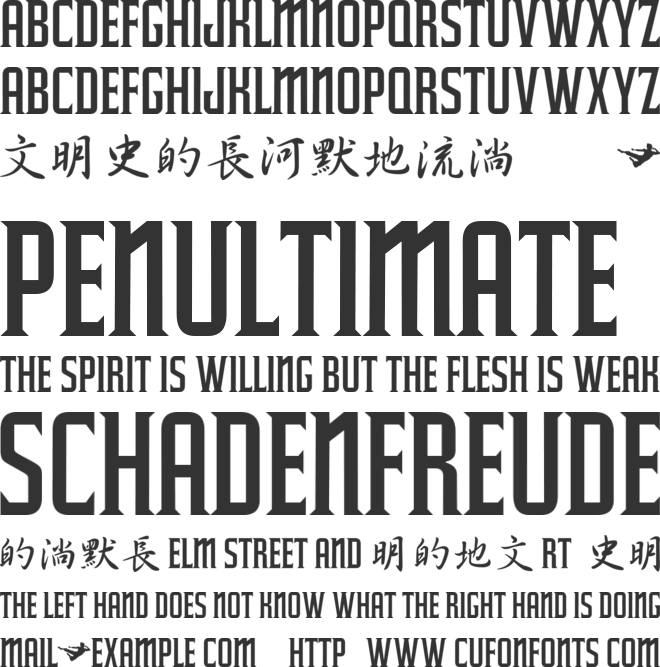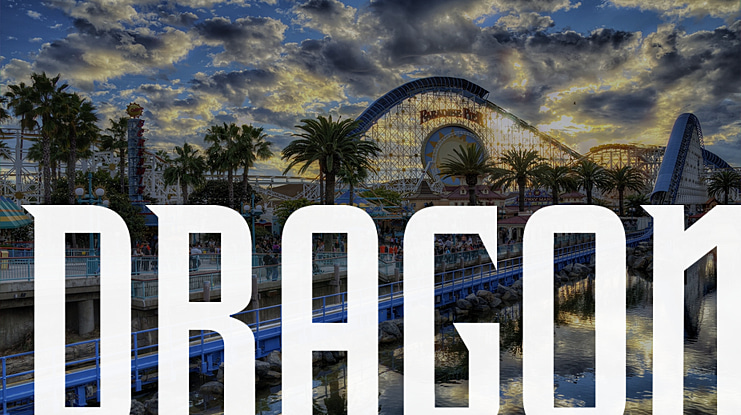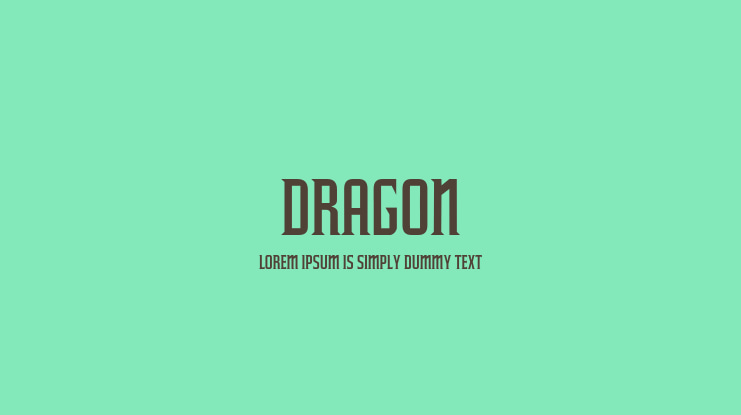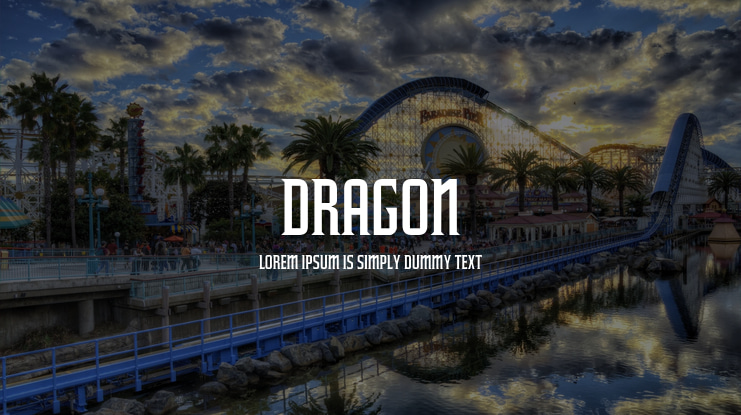
DRAGON Font
P.A.Vannucci
Direttamente dal film diretto da Rob Cohen e interpretato da Jason Scott Lee, il font inedito per tutti gli estimatori del film.
Directly from the film directed by Rob Cohen and starring Jason Scott Lee, the new font for all admirers of the film.